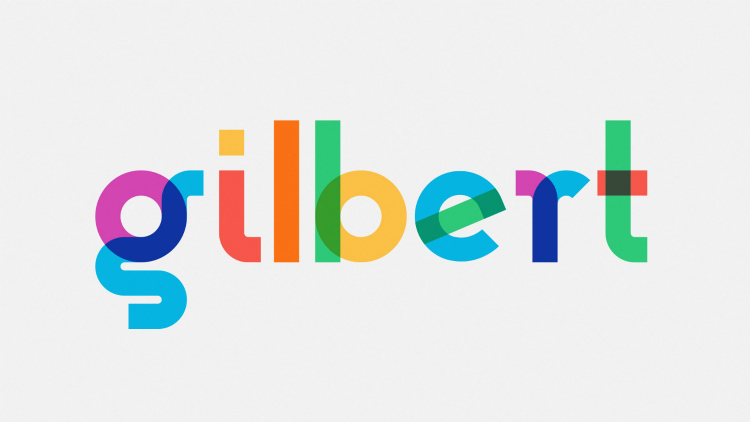
Gilbert, es el verdadero nombre que recibe este diseño de tipografía realizado por los agencia Ogilvy & Mather y Fontself para NewFest y el NYC Pride; las cuales, buscan crear una mayor presencia digital del orgullo y apoyo a la comunidad LGBTQ.
Type With Pride, es básicamente el mensaje que este diseño busca llevar al mundo; esto debido a que este diseño a grosso modo busca lograr que todo el mundo pueda “escribir con orgullo“.
Sin duda, un peculiar diseño que representa muy bien los colores de la bandera de la comunidad LGBTQ; mismo que recibe su nombre (Gilbert) con motivo del fallecimiento del creador de esta bandera.